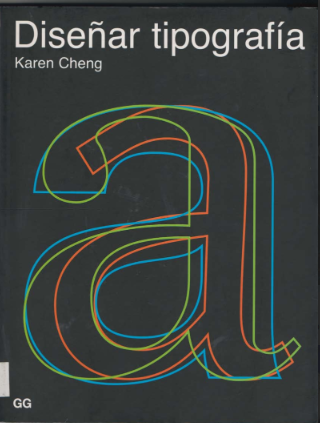
Diseñar Tipografía
يُطرح منتج رقمي بعنوان Diseñar Tipografía في صورة كتاب إلكتروني يفتح الباب أمام القارئ لاكتشاف العالم الدقيق والمعقّد لفن تصميم الحروف، ذلك الفن الذي يجمع بين الإبداع الفني والدقة التقنية ليُنتج أنظمة كتابية تحمل طابعًا مميزًا وهوية خاصة. هذا المنتج الرقمي لا يُقدَّم كمجرد دليل تقني عن تصميم الحروف، بل هو رحلة معرفية تساعد القارئ على فهم كيف تتحول الخطوط والنِسب والفراغات إلى لغة بصرية متكاملة قادرة على التواصل والإلهام.
إن Diseñar Tipografía كمنتج رقمي يُسلط الضوء على مختلف المراحل التي يمر بها تصميم الحروف، بدءًا من الفكرة الأولى ورسم النماذج الأولية (sketches)، مرورًا بتطوير الحروف الرقمية وضبط التفاصيل الدقيقة مثل التباعد والانسجام البصري، وصولًا إلى إنشاء عائلة طباعية متكاملة يمكن استخدامها في مشاريع متعددة. ومن خلال هذا الكتاب الإلكتروني، يدرك القارئ أن تصميم الخطوط ليس مجرد ممارسة جمالية، بل هو مسؤولية تواصلية، حيث تؤثر كل تفاصيل الحرف في طريقة إدراك النص وفهم رسالته.
إن القيمة الحقيقية لهذا المنتج الرقمي تكمن في أنه يفتح أمام القارئ وعيًا جديدًا بجماليات الحرف ودوره المحوري في التصميم، حيث يصبح النص أكثر من مجرد كلمات مقروءة، بل تجربة بصرية متكاملة. وهكذا، فإن Diseñar Tipografía يمثّل منتجًا رقميًا ثريًا يُلهم القارئ للنظر إلى الحروف كعناصر تصميمية حيّة تحمل في داخلها الفن، الثقافة، والهوية.